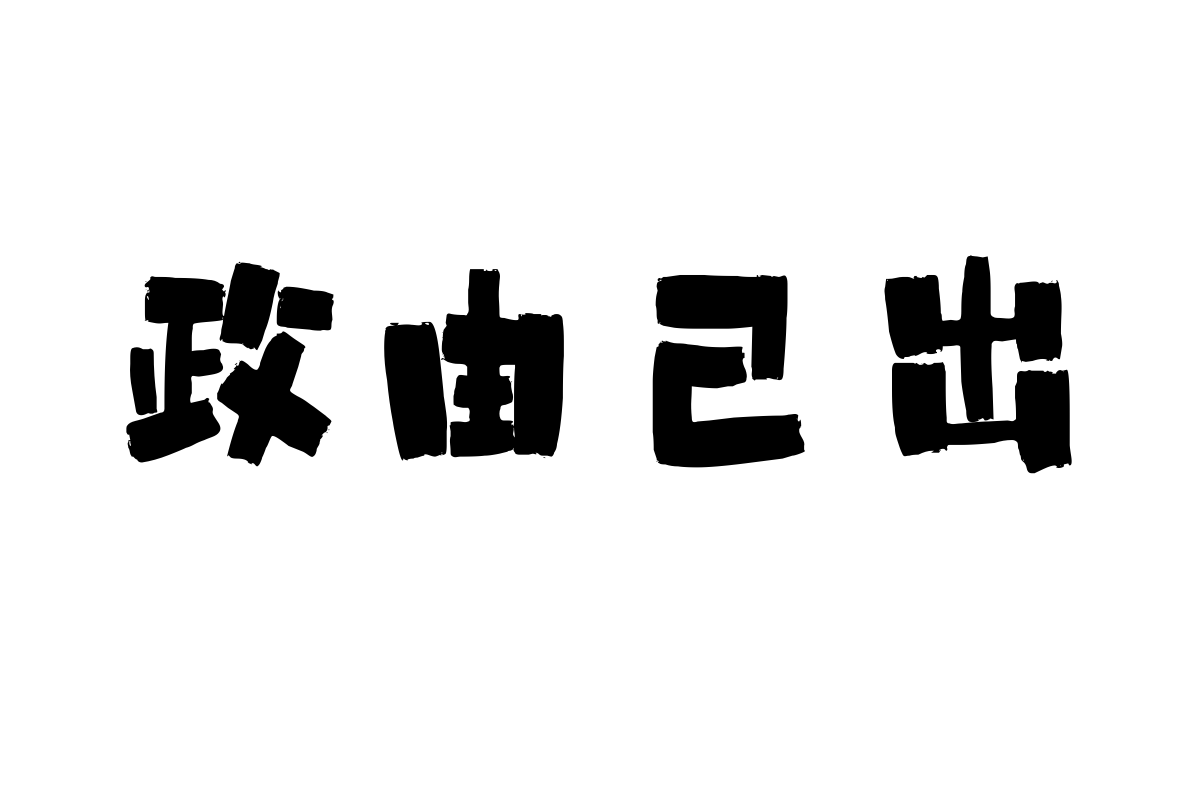
三极初上体,又称“三极体”,是一种古老的字体风格,起源于中国古代。这种字体的特点是笔画粗细不一,呈现出一种独特的美感。它主要用于书法和篆刻等领域,具有很高的艺术价值和文化内涵。
三极初上体的笔画特点是:笔画粗细不均,线条流畅自然,富有变化。这种字体的书写需要一定的技巧和经验,但一旦掌握,便能展现出其独特的魅力。
此外,三极初上体还具有一定的实用性。在古代,人们常常用这种字体来制作印章、碑文等,以增加作品的艺术感。同时,由于其独特的视觉效果,也常被用于装饰品、艺术品等的设计与制作中。